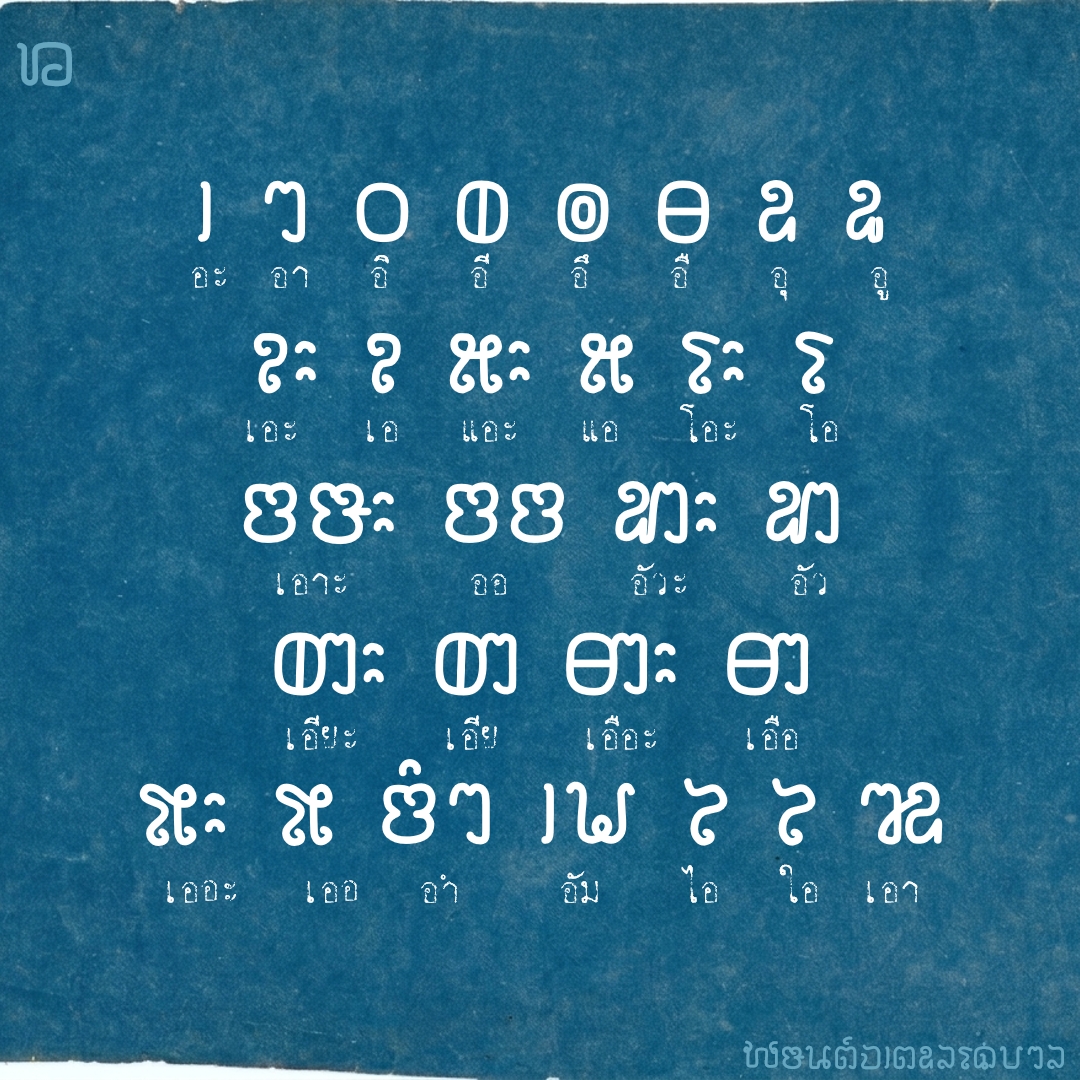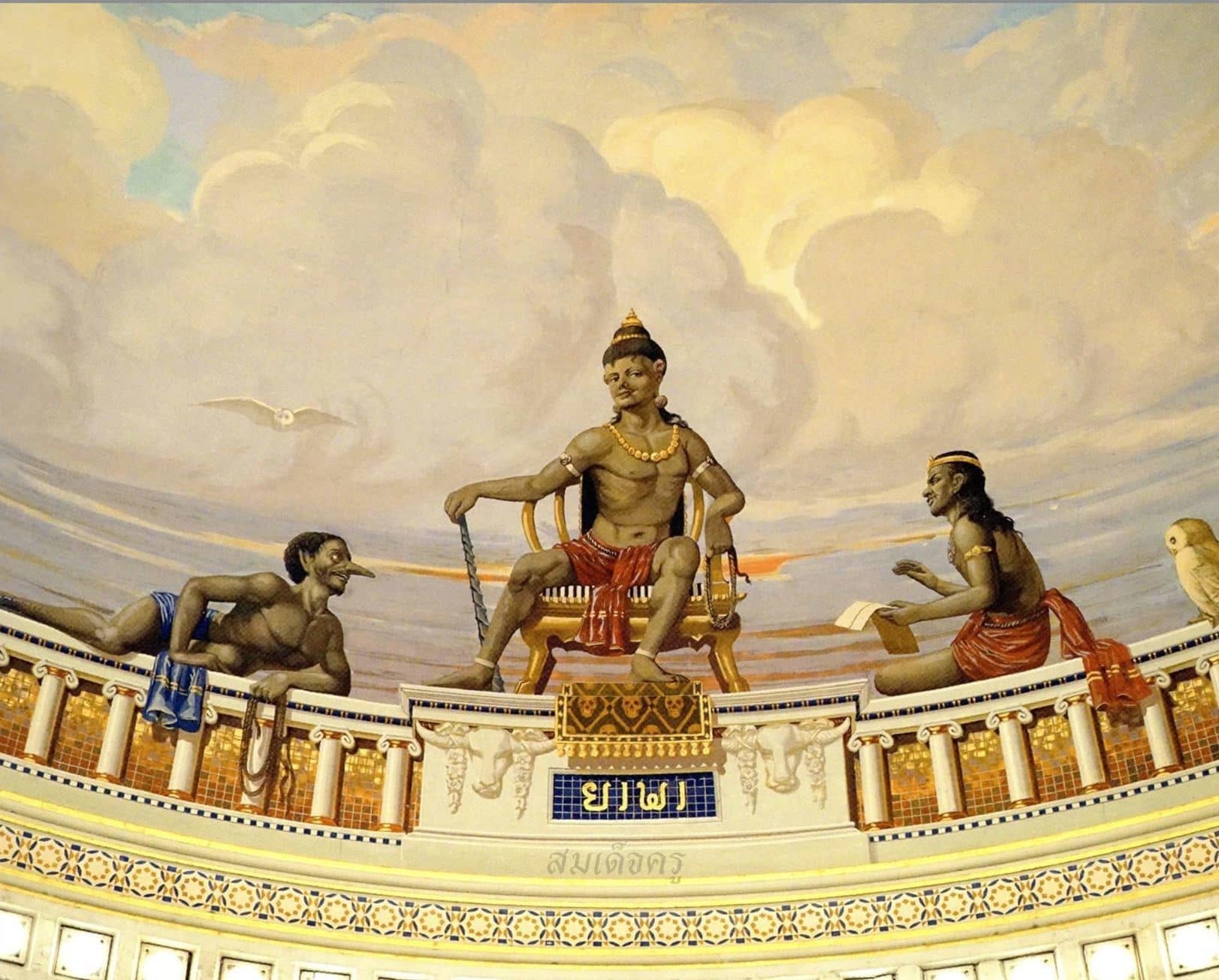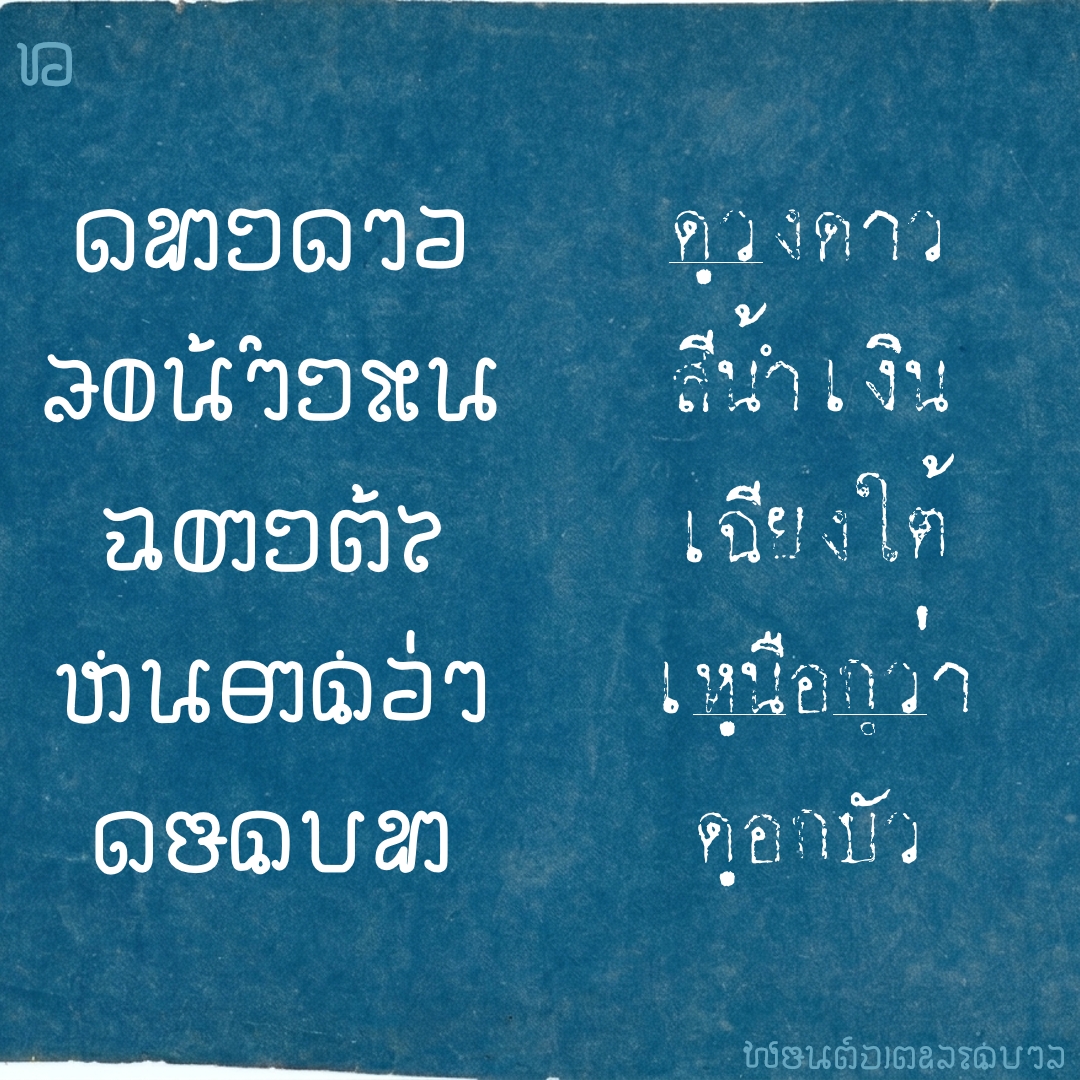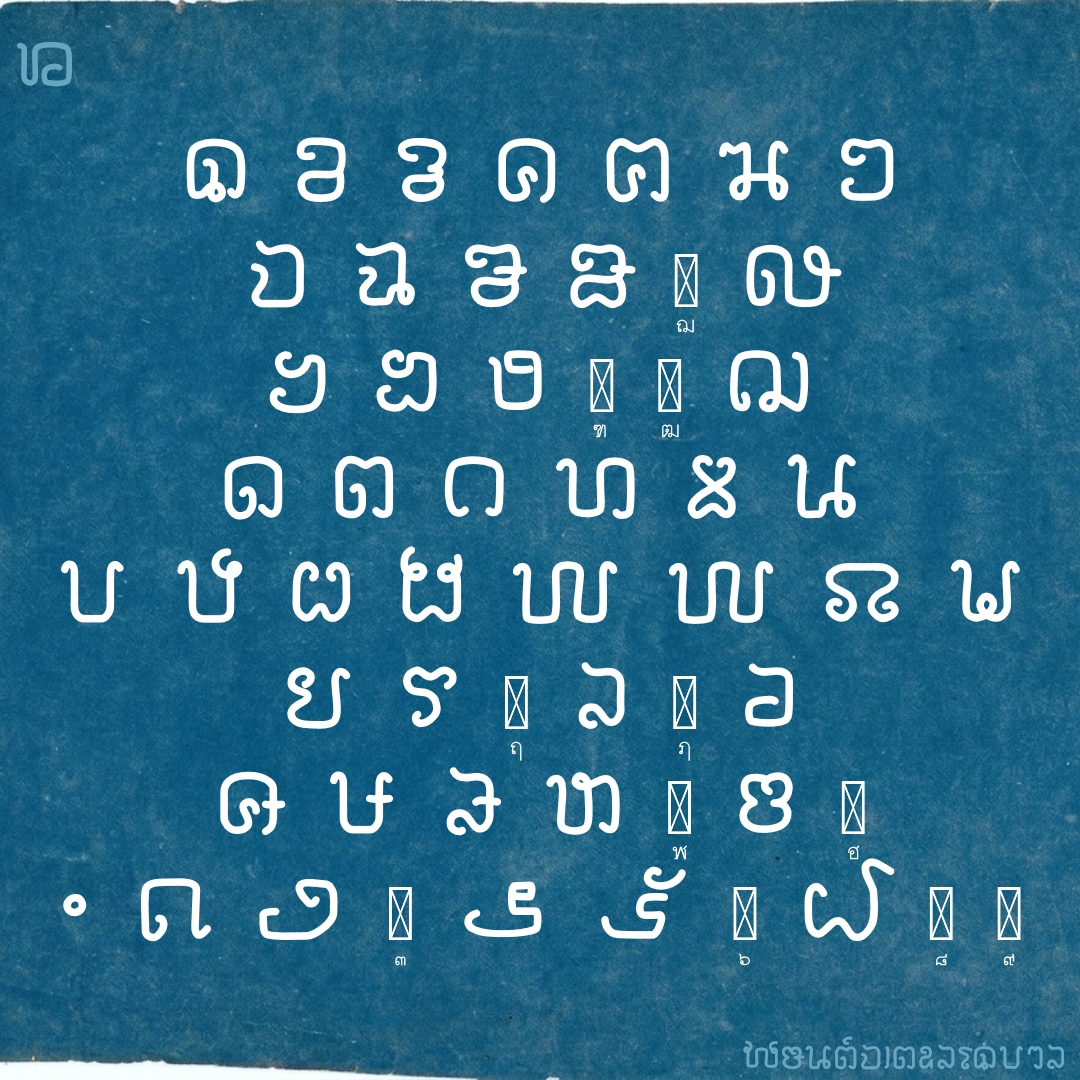
ฟอนต์ จตุโลกบาล
ฟอนต์นี้ได้แนวคิดจาก ตัวอักษรในภาพจตุโลกบาล ของสมเด็จครู ในพระที่นั่งบรมพิมาน ..พยัญชนะของพ่อขุนรามฯ สระและวิธีเขียนจากอักขรวิธีใหม่ของ ร.6 แต่พิมพ์แบบฟอนต์ไทยปรกติ เดี๋ยวฟอนต์จัดการสระให้เอง ยกเว้นแต่สระลดรูป และอักษรควบ ต้องใช้พินทุช่วย(ดูจากรูปตัวอย่าง)
ตัวอย่างอักษร
แพนแกรม..ลองอ่านลองเดาดู
วิธีพิมพ์
ชื่อฟอนต์ : จตุโลกบาล
ฟอนต์นี้ได้แนวคิดจาก ตัวอักษรในภาพจตุโลกบาล ของสมเด็จครู ในพระที่นั่งบรมพิมาน ..พยัญชนะของพ่อขุนรามฯ สระและวิธีเขียนจากอักขรวิธีใหม่ของ ร.6 แต่พิมพ์แบบฟอนต์ไทยปรกติ เดี๋ยวฟอนต์จัดการสระให้เอง ยกเว้นแต่สระลดรูป และอักษรควบ ต้องใช้พินทุช่วย(ดูจากรูปตัวอย่าง)